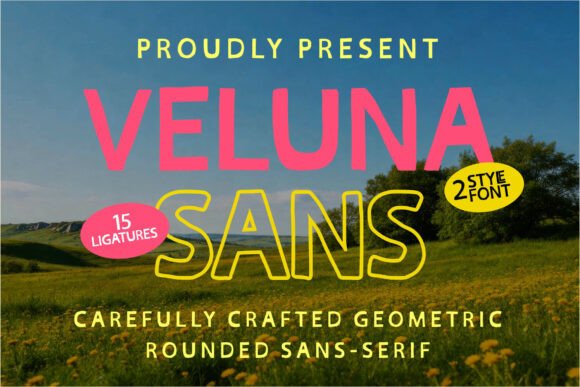
Veluna Sans
Mencari elemen reka bentuk yang sesuai boleh menjadi mencabar, tetapi Veluna Sans menawarkan koleksi luar biasa yang menaik taraf karya anda serta-merta.
Dicipta dengan ketepatan, Veluna Sans menyediakan vektor yang bersih, tipografi yang licin dan lesen komersial untuk ketenangan fikiran.